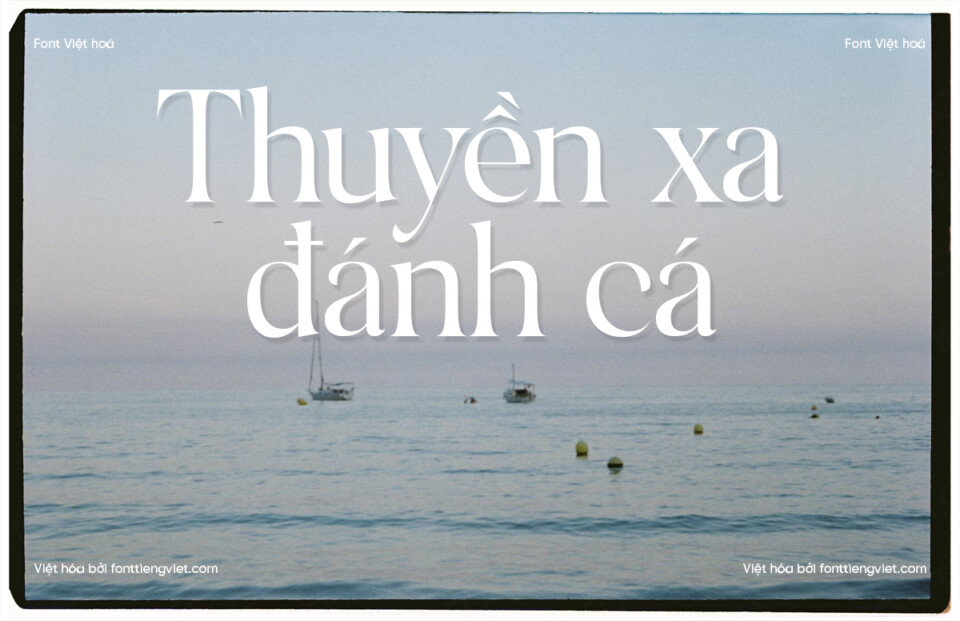
Font Việt hóa 1FTV VIP Qalogre
Font Việt hóa 1FTV VIP Qalogre: Bộ Font Sang Trọng Cho Thiết Kế Chuyên Nghiệp
Trong thế giới thiết kế đồ họa hiện đại, việc lựa chọn một bộ Font Miễn Phí phù hợp chính là chìa khóa để tạo nên sự khác biệt và ấn tượng mạnh mẽ cho tác phẩm. Một trong những cái tên đang thu hút sự chú ý của cộng đồng designer chính là Font Việt hóa 1FTV VIP Qalogre. Đây là một bộ font chữ mang phong cách hiện đại, thanh lịch nhưng không kém phần phá cách, rất phù hợp cho các dự án đòi hỏi tính thẩm mỹ cao và sự chuyên nghiệp tuyệt đối. Với khả năng tương thích tốt và hiển thị sắc nét trên nhiều thiết bị, bộ font này đang dần trở thành công cụ hỗ trợ đắc lực cho người dùng tại Việt Nam.
Tìm hiểu về đặc điểm của Font Việt hóa 1FTV VIP Qalogre
Phong cách thiết kế và tính ứng dụng
Bộ Font Việt hóa 1FTV VIP Qalogre sở hữu các đường nét thanh mảnh kết hợp với những khúc bo tròn tinh tế, tạo nên một tổng thể hài hòa và sang trọng. Điểm đặc biệt của bộ font này chính là sự linh hoạt trong ứng dụng thực tế. Bạn có thể sử dụng nó cho các thiết kế nhận diện thương hiệu, thiết kế bao bì sản phẩm cao cấp hoặc các ấn phẩm truyền thông xã hội. Với bộ ký tự được việt hóa hoàn chỉnh, người dùng sẽ không còn lo lắng về lỗi font hay thiếu dấu khi gõ tiếng Việt, từ đó giúp quy trình làm việc trở nên mượt mà và hiệu quả hơn rất nhiều.
Lý do bạn nên sở hữu bộ font này
Việc sử dụng Font Việt hóa 1FTV VIP Qalogre mang lại nhiều lợi ích thiết thực cho người dùng. Thứ nhất, nó giúp nâng tầm giá trị cho các bản thiết kế, làm cho nội dung trở nên dễ đọc và bắt mắt hơn. Thứ hai, đây là lựa chọn tối ưu cho những ai yêu thích phong cách tối giản (minimalism) nhưng vẫn muốn giữ được nét cá tính riêng biệt. Ngoài ra, bộ font này đã được tối ưu hóa về mặt kỹ thuật, đảm bảo độ hiển thị tốt nhất trên cả các nền tảng web và in ấn truyền thống, giúp thông điệp của bạn luôn được truyền tải một cách trọn vẹn nhất đến khách hàng.
Lưu ý khi phối hợp font chữ
Để phát huy tối đa vẻ đẹp của Font Việt hóa 1FTV VIP Qalogre, bạn nên chú ý đến việc phối hợp với các kiểu chữ khác. Một quy tắc vàng trong thiết kế là không nên sử dụng quá nhiều font chữ trong cùng một ấn phẩm. Bạn có thể kết hợp Qalogre cho các tiêu đề (Heading) chính để tạo điểm nhấn, và sử dụng các font chữ không chân (Sans Serif) đơn giản cho phần nội dung chi tiết. Sự kết hợp này sẽ tạo ra một cấu trúc thị giác rõ ràng, giúp người xem dễ dàng tiếp nhận thông tin và cảm nhận được sự tinh tế trong phong cách nghệ thuật mà bạn đang theo đuổi.
Kết luận về bộ Font Việt hóa 1FTV VIP Qalogre